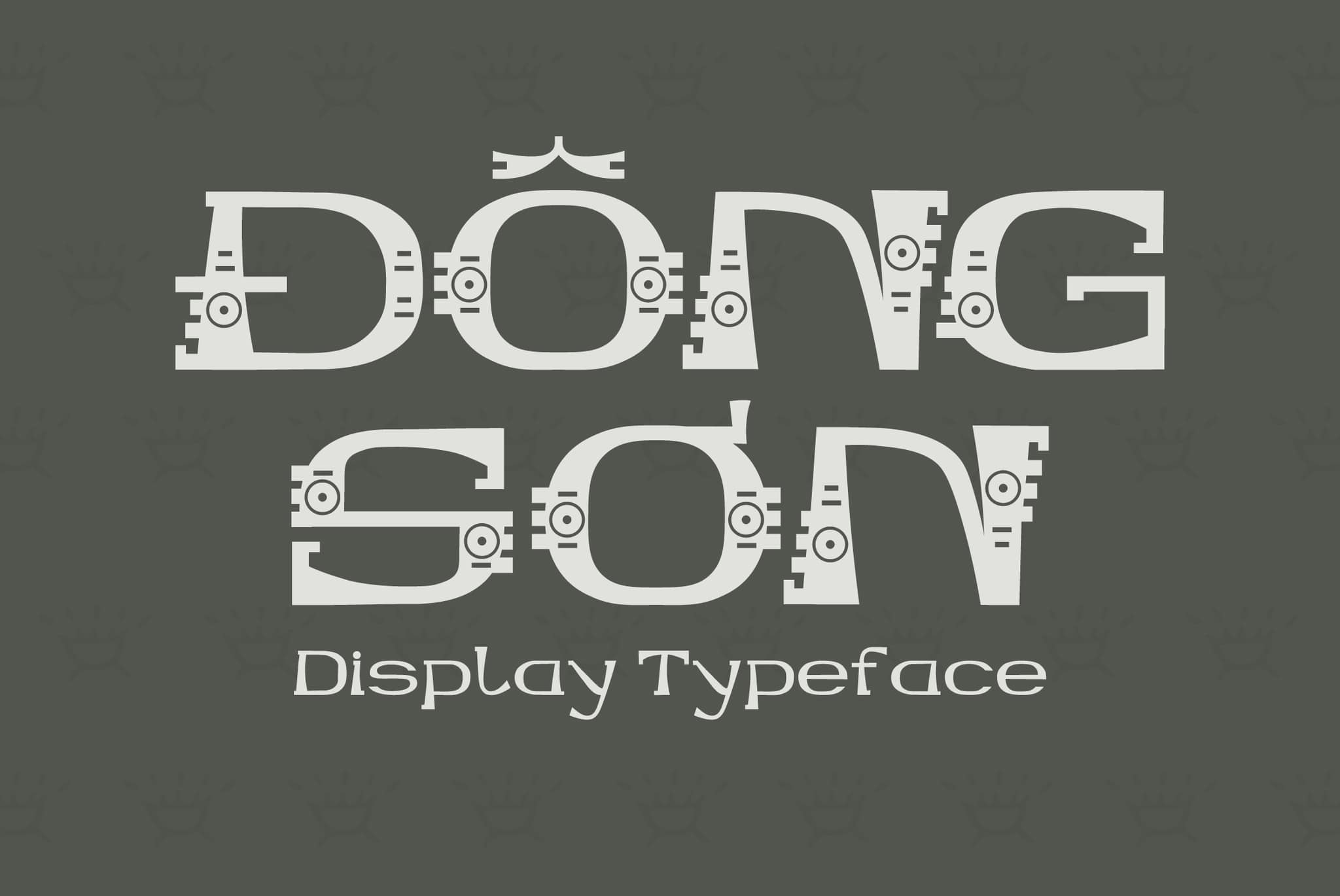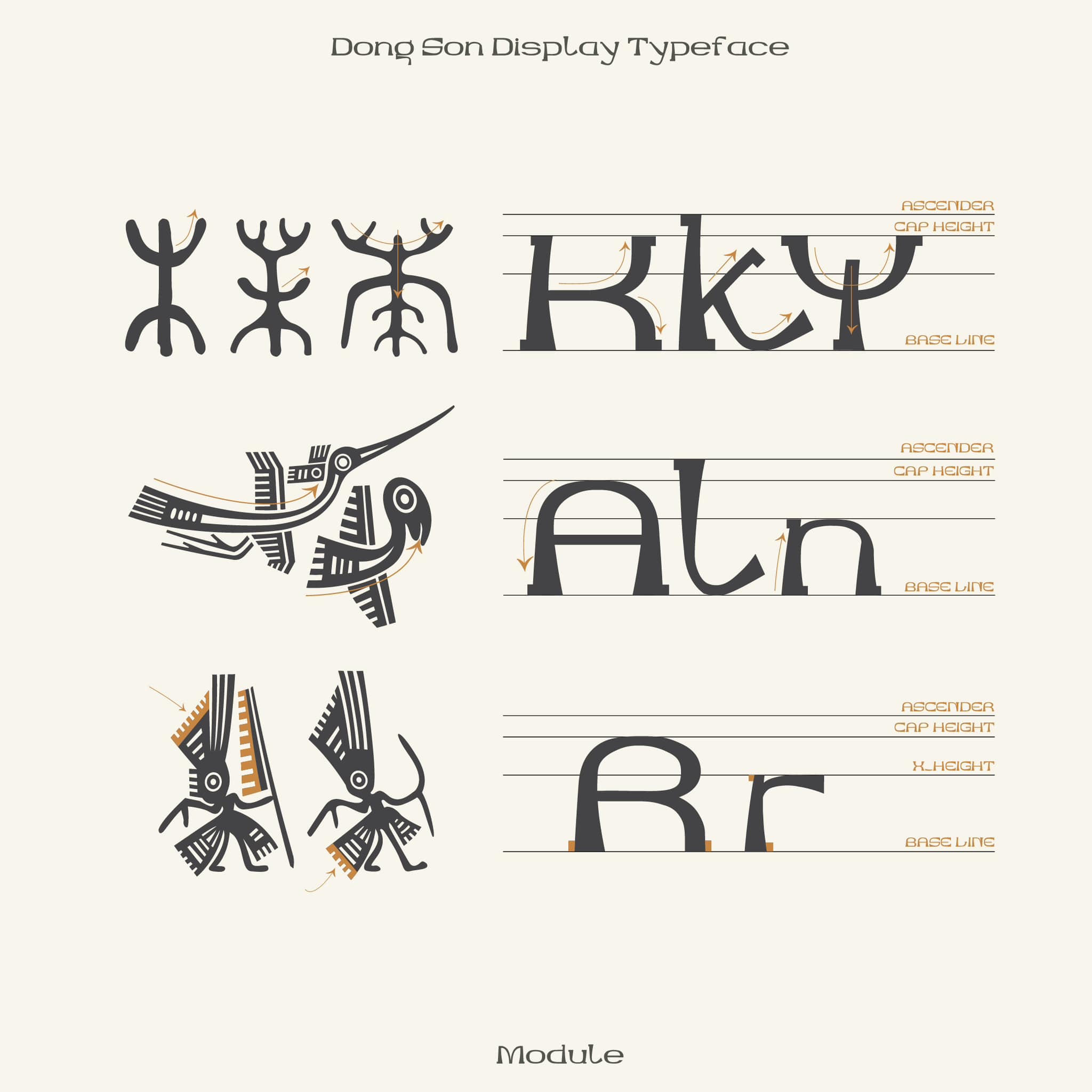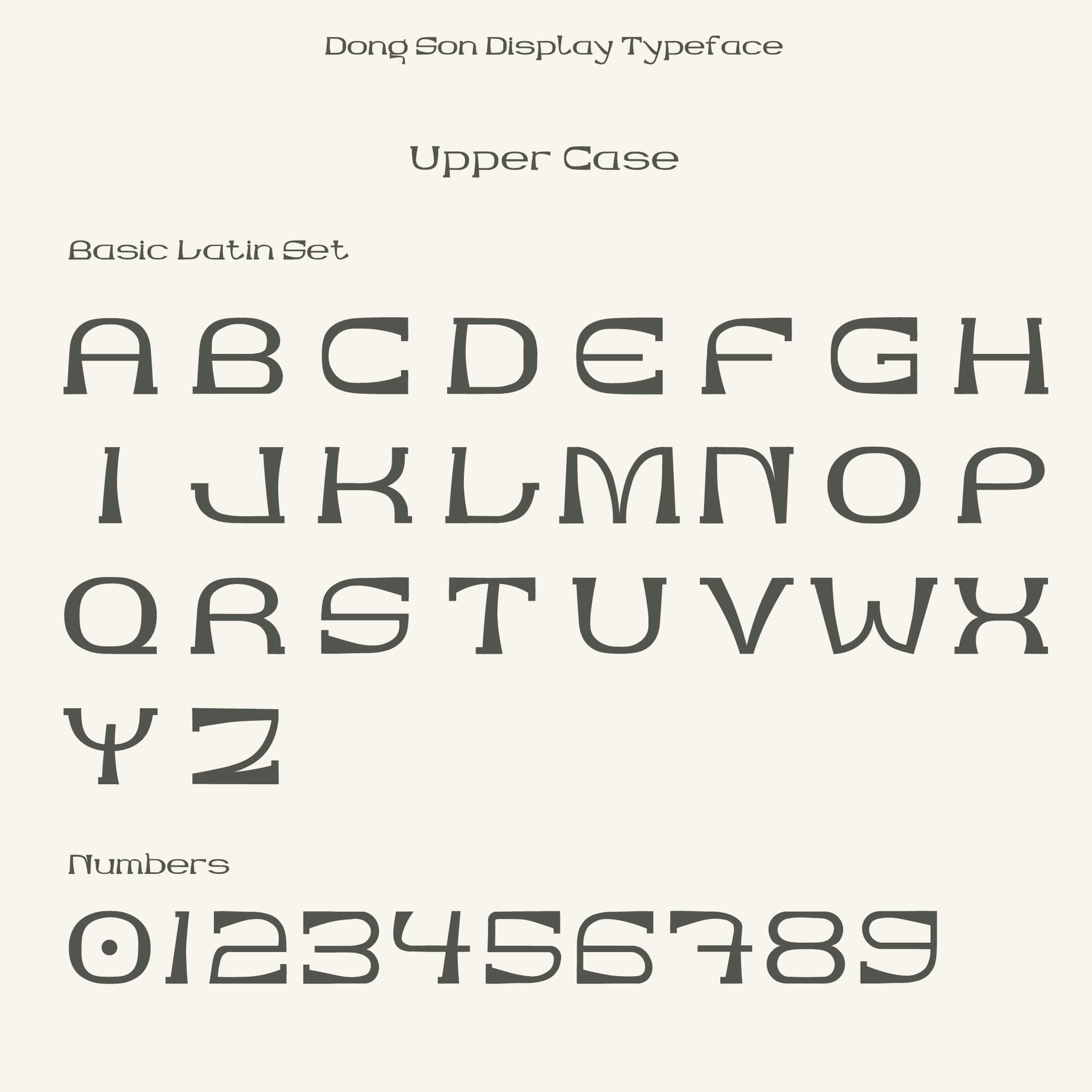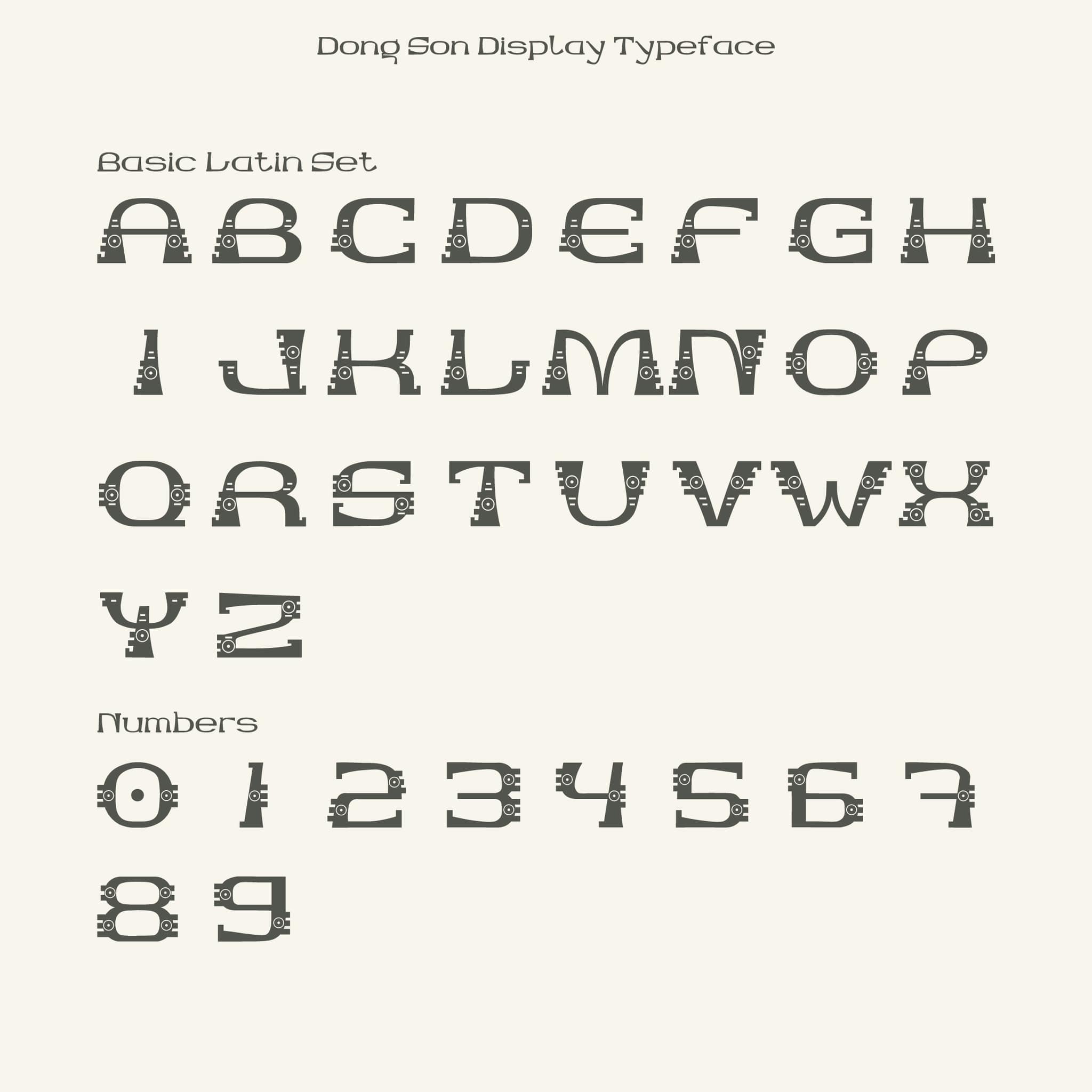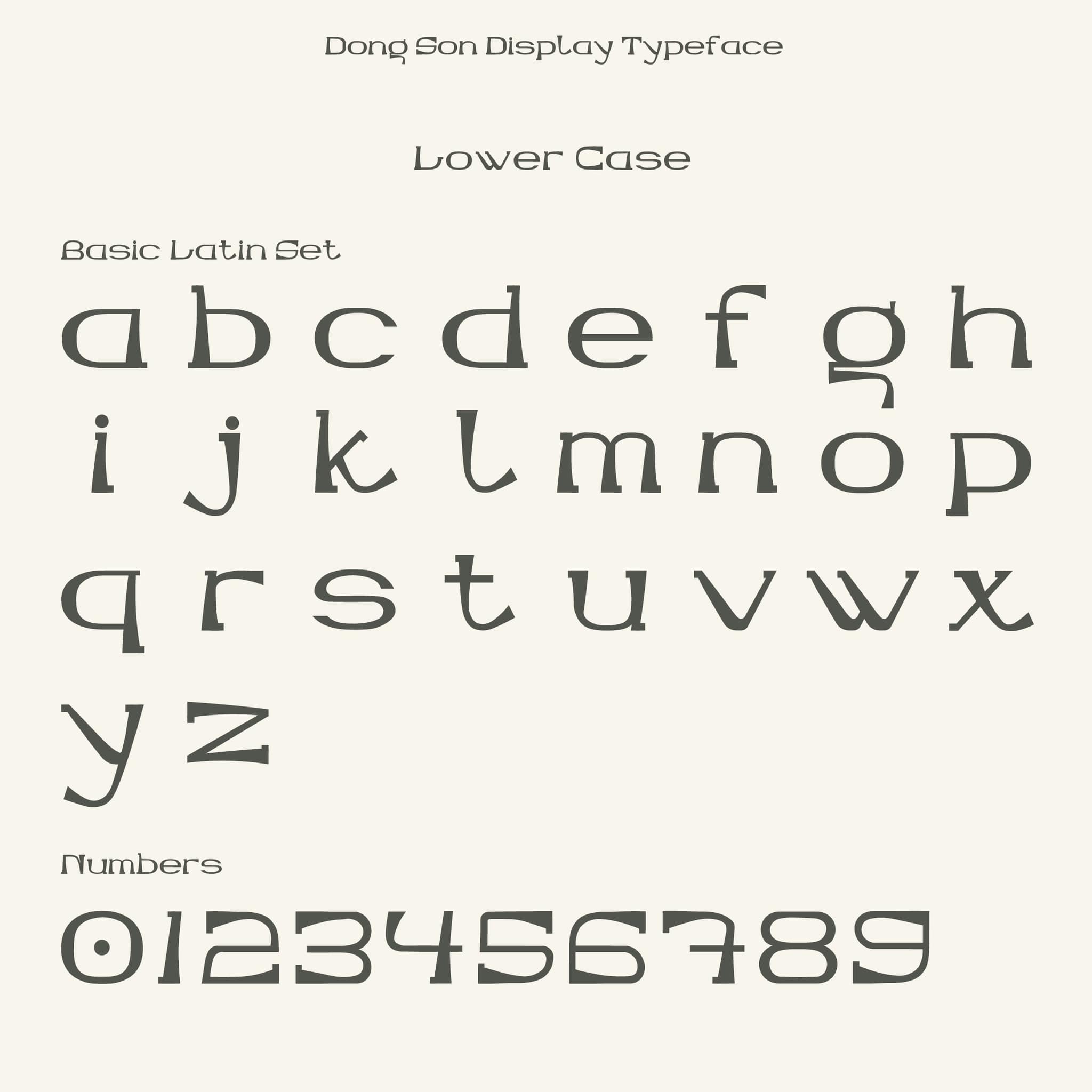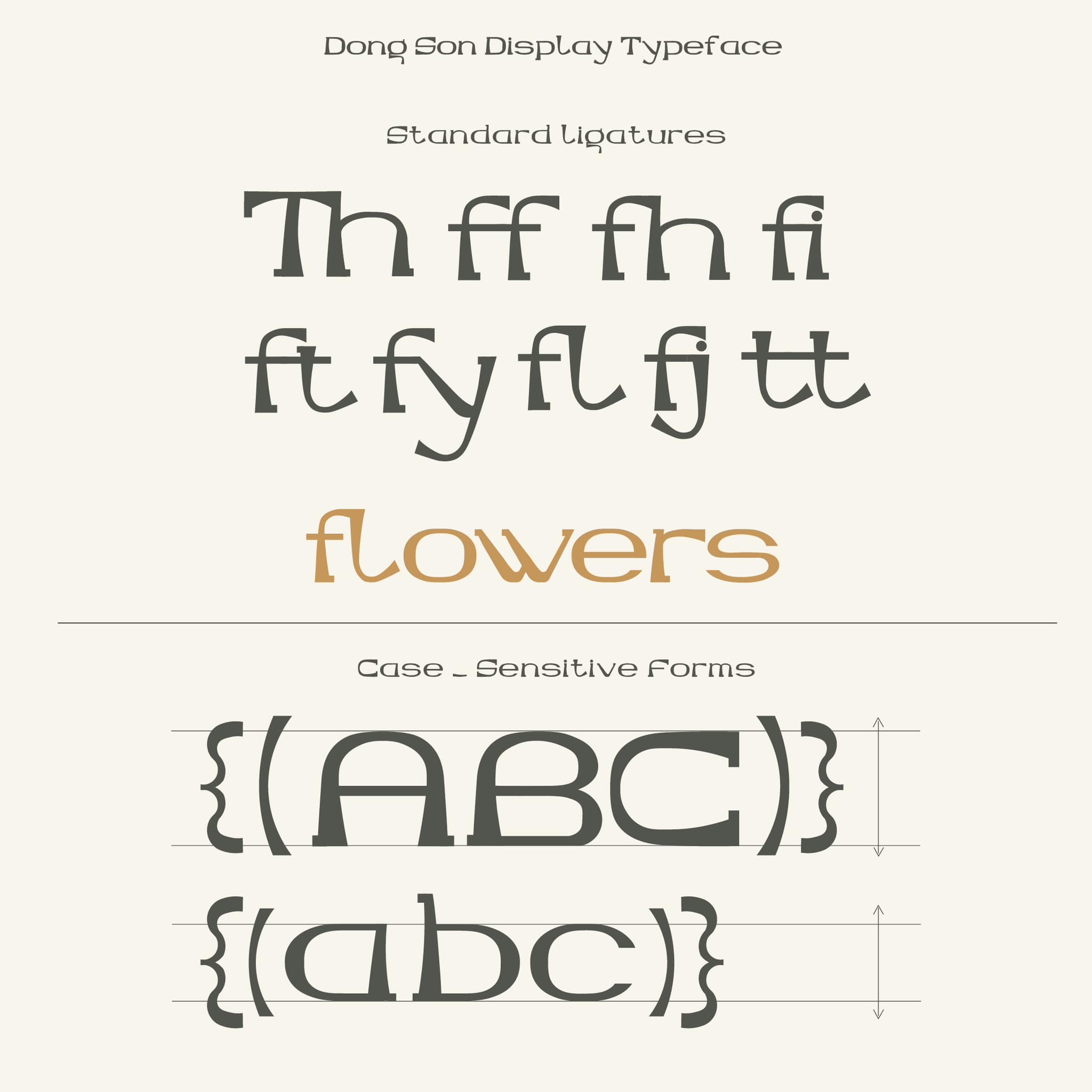
Đông Sơn Display Typeface: Tái Hiện Hồn Thiêng Sông Núi Qua Ngôn Ngữ Typography Hiện Đại
Trong dòng chảy của thiết kế hiện đại, việc tìm về cội nguồn văn hóa để khai thác chất liệu sáng tạo đang trở thành một xu hướng đầy cảm hứng. Đồ án tốt nghiệp Dong Son Display Typeface của tác giả Hải Yến là một minh chứng xuất sắc cho sự giao thoa đó. Hãy cùng Piklab giải mã ngôn ngữ thiết kế độc đáo của bộ Typeface mang đậm hồn Việt này.
Lấy cảm hứng từ sự tinh xảo ấy, Đông Sơn Display Typeface không sao chép rập khuôn mà chắt lọc những đường nét đặc trưng nhất:
- Chim Lạc: Biểu tượng cho khát vọng bay cao.
- Hình ngôi sao và vòng tròn đồng tâm: Tượng trưng cho mặt trời và sự vần xoay của vũ trụ.
- Họa tiết kỷ hà: Những đường vạch ngắn, tam giác răng cưa thể hiện trang phục và đời sống sinh hoạt.
Điều làm nên sự đặc biệt của bộ Typeface chính là tư duy hình khối (module). Tác giả Hải Yến đã khéo léo xử lý các nét chữ dựa trên cấu trúc hình học của họa tiết gốc.
Một điểm sáng tạo đáng khen ngợi là hệ thống dấu tiếng Việt. Thay vì dùng các dấu sắc, huyền, hỏi, ngã thông thường, tác giả đã cách điệu chúng thành hình dáng của những con thuyền, cánh chim hoặc họa tiết lông công. Điều này tạo nên sự đồng bộ tuyệt đối về mặt thị giác cho toàn bộ văn bản.
Dự án đã chứng minh rằng: Văn hóa truyền thống chưa bao giờ cũ, nó chỉ đang chờ những nhà thiết kế trẻ "đánh thức" bằng một ngôn ngữ mới – ngôn ngữ của Typography.